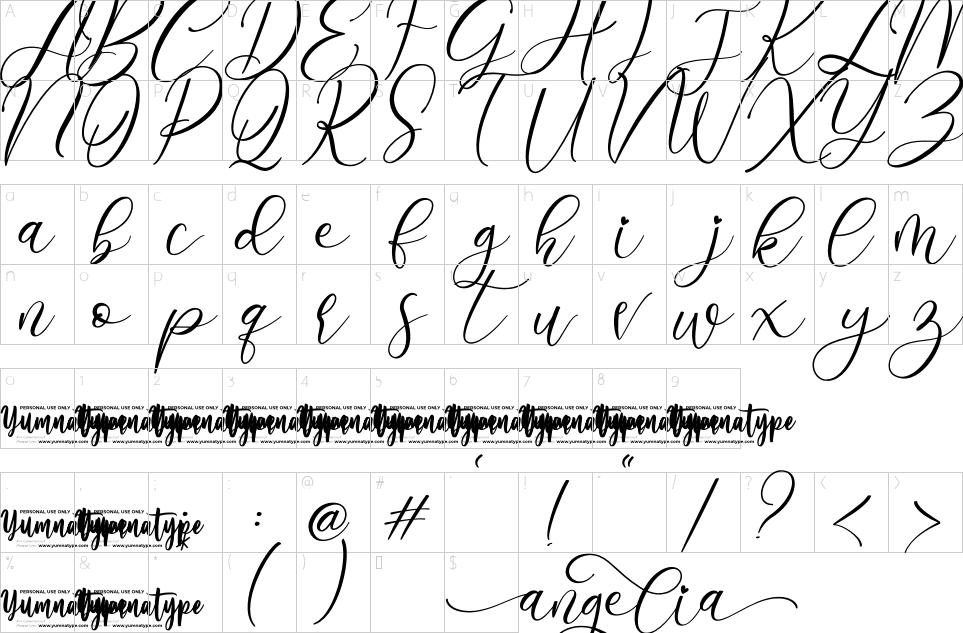
Angelia Font – Download Grátis
Descubra a beleza da Angelia font, uma elegante e delicada fonte gráfica gratuita. Desenvolvida pelo Yumna Type, Angelia oferece um charme único que é perfeito para projetos de design. Esta fonte tem sido descarregada 3.047 vezes, demonstrando sua popularidade entre designers que valorizam o seu estilo fluido e confortável. A Angelia é uma excelente escolha para designers de sites, designers de marca e designers de publicidade. Seja você um estudante de design ou profissional, a Angelia é uma fonte que merece estar em seu arsenal de recursos gráficos. Descubra a beleza da Angelia e traga mais vida e personalidade para seus projetos.